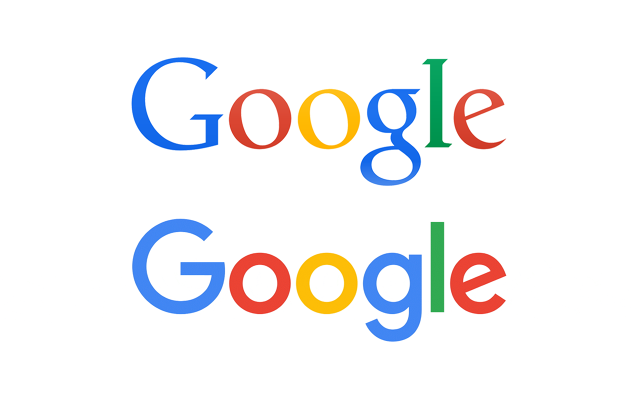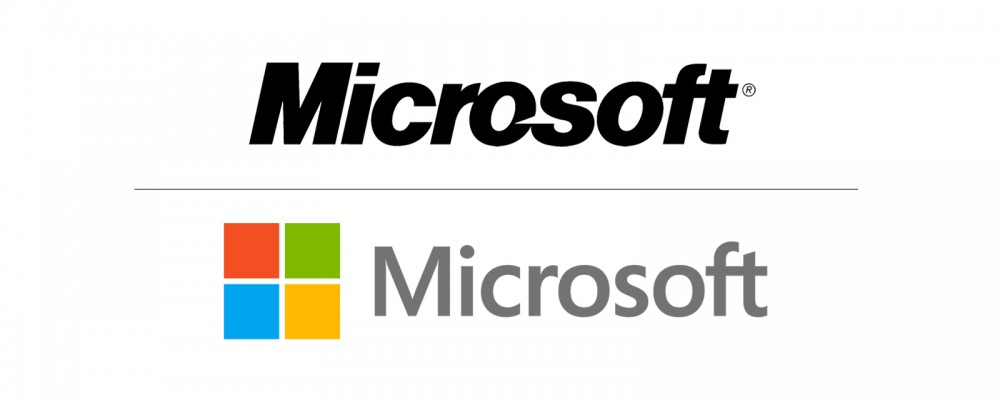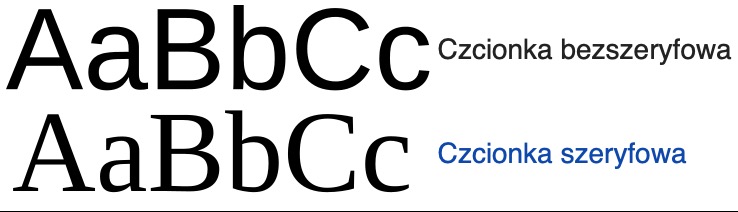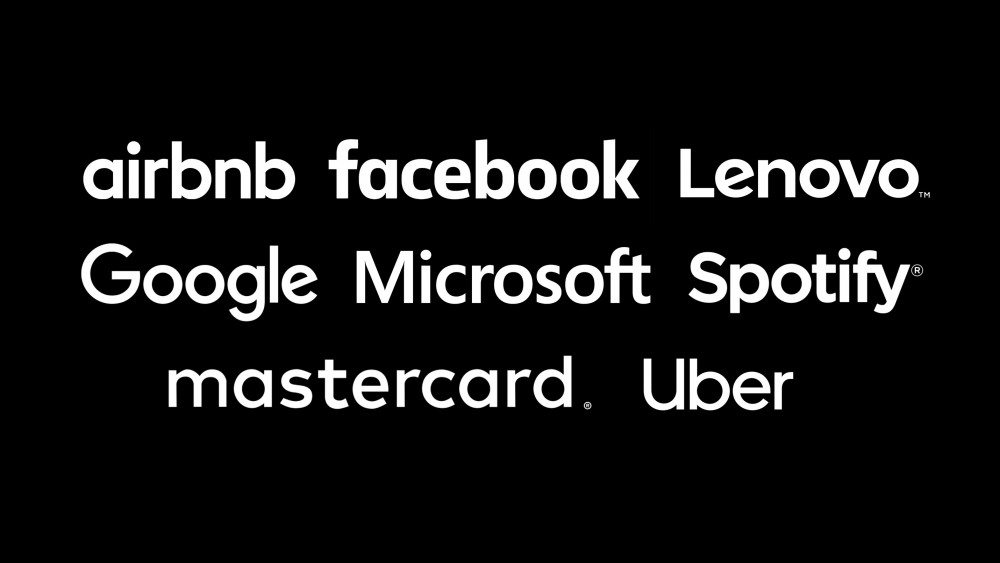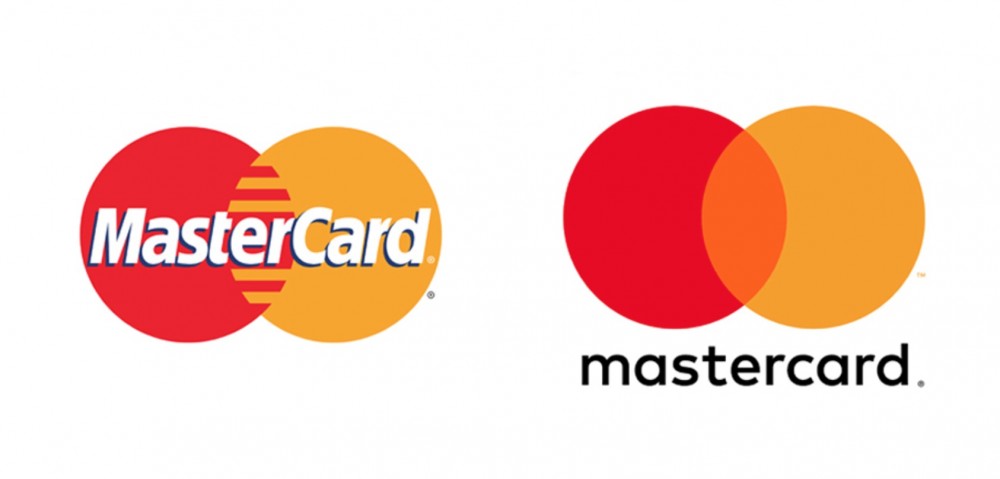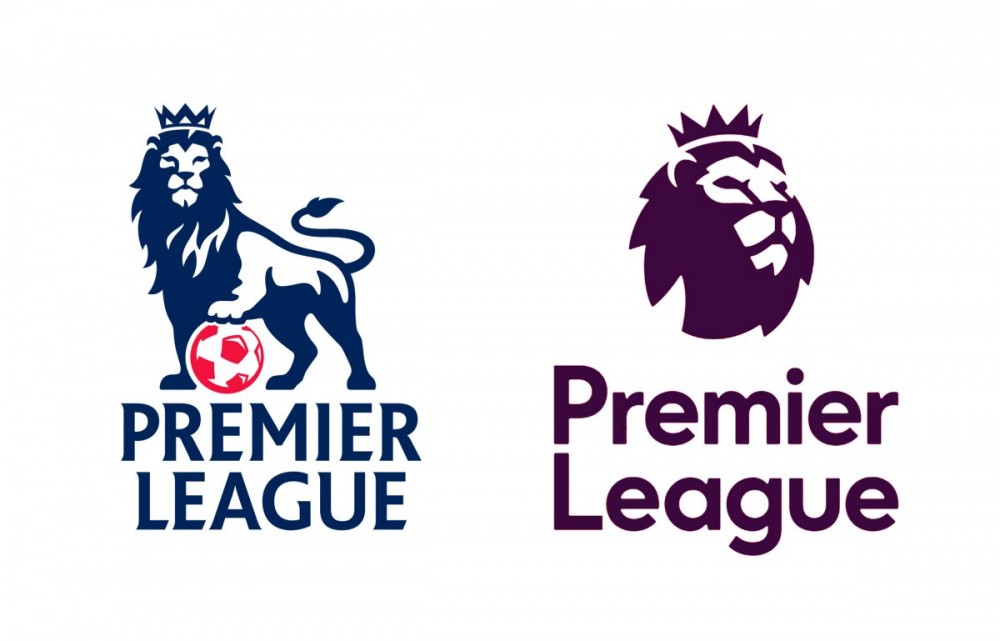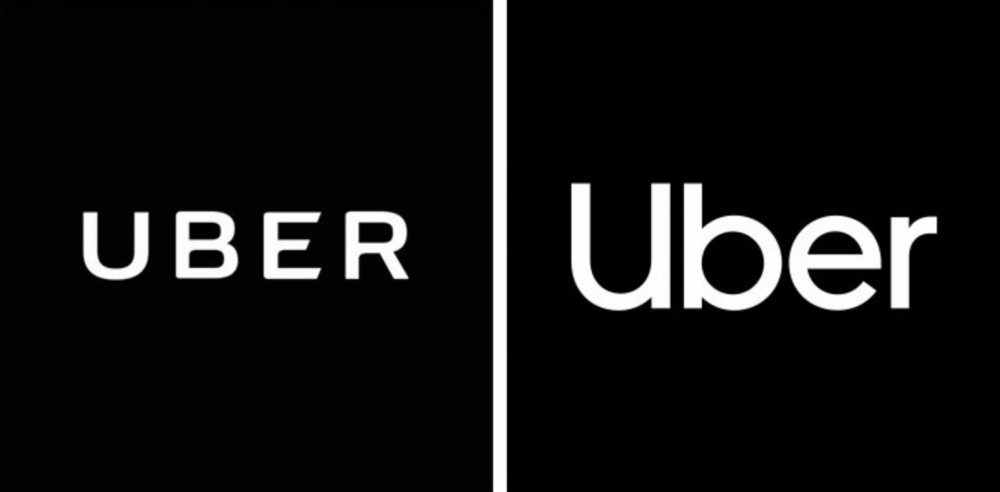
Dlaczego wszystkie nowe logotypy wyglądają tak samo?
Czy zastanawialiście się, dlaczego tak wiele firm decyduje się na uproszczenie swojego logo? Nie ma kwartału, by nie słyszeć o  rebrandingu dużej firmy. Nowe logotypy dążą do jednej wspólnej stylistyki, ale właściwie, dlaczego tak się dzieje?
Dlaczego wszystkie nowe logotypy wyglądają tak samo?
Niedawno napisał do nas czytelnik, będący project managerem w agencji reklamowej Upside. Agencja od 2010 r. posługuje się logo stworzonym przez dyrektora kreatywnego agencji.
Pojawił się jednak problem. Jak pisze project manager, hollywoodzka produkcja „The Upside” promuje się bardzo podobnym logo do agencji. W mailu pada stwierdzenie o „dokładnie takim samym znaku”, choć widać między nimi różnice. Film „The Upside” trafi na ekrany kin w 2019 r. i będzie amerykańską wariacją na temat francuskiego hitu „Nietykalni” z 2011 r.
Logo agencji wygląda następująco.
A tak prezentuje się wygląd materiałów promujących film.
Podobieństwo jest znaczące, ale czy można mówić o plagiacie?
Sądowe dochodzenie swoich praw może być w tym przypadku bardzo trudne. Oba logotypy są podobne, ale podobieństwo wynika z bardzo zbliżonego, niemal identycznego kroju pisma.
Sprawa jest o tyle ciekawa, że oba podmioty zastosowały najmodniejszą w ostatnich latach stylistykę, która jest chętnie wykorzystywana przez wiele firm, w tym przez największych gigantów świata IT. Do tego mamy identyczną nazwę, ale jest to najpewniej dziełem przypadku.
Ochrona logo firmy wynika wprost z prawa autorskiego i jest przyznawana na mocy ustawy, bez konieczności rejestracji znaku. Można też dodatkowo zarejestrować logo w urzędzie patentowym jako znak towarowy, ale nawet to nie chroni firmy w pełni, ponieważ ochrona tyczy wykorzystania logo w podobnych towarach lub usługach. Jeśli dwie agencje reklamowe miałyby bardzo podobne logo, można byłoby skutecznie dochodzić swoich praw. Co innego, gdy mówimy o agencji i filmie.
Logotypy dzisiejszych firm trudno od siebie odróżnić.
Tylko spójrzcie na zestawienie, które przygotowałem.
Takich przykładów jest znacznie więcej. Mamy różne grubości fontów, ale logotypy pozbawione sygnetu są do siebie niebywale podobne. Nie ma w tym żadnego przypadku. Coraz więcej firm przechodzi rebranding, który zbliża logotypy do jednej, wspólnej stylistyki. Spójrzcie tylko na kilka przykładów z ostatnich lat.
Dlaczego logotypy są do siebie tak podobne?
W pierwszej chwili można pomyśleć, że nadmierne upraszczanie bierze się z chęci oszczędności, bo przecież ile może kosztować zaprojektowanie zwykłego napisu zrobionego fontem Arial, lub podobnym bezszeryfowym krojem? To błędna logika, bo koszty rebrandingu w dużych firmach IT są przepotężne, nawet jeśli zmiany są niewielkie.
Różnica między fontem bezszeryfowym i szeryfowym; źródło: Wikipedia.
Skąd w takim razie podobieństwo logotypów? W dużej mierze wynika to z popularyzacji smartfonów. Dawniej logotypy były pokazywane na wydrukach, na banerach, czy w siedzibach firm. Później trafiły do internetu, ale były oglądane na dość sporych ekranach komputerów. Wszystko zmieniło się w erze mobilnej. Nagle logotypy muszą wyglądać świetnie na bardzo małych powierzchniach. Fragment górnej belki strony internetowej może mieć na smartfonie mniej niż centymetr, a logo na tym obszarze musi być czytelne i rozpoznawalne.
Co więcej, logo musi być wyraźne na przeróżnych konfiguracjach przekątnej ekranu i rozdzielczości. Musi wyglądać świetnie zarówno na nowoczesnym smartfonie z ekranem o kosmicznym zagęszczeniu pikseli, jak i na starszym urządzeniu, gdzie piksele są widoczne gołym okiem.
Jest to główny powód przechodzenia na bezszeryfowe fonty o podobnej stylistyce. Taki krój po prostu sprawdza się w dzisiejszym świecie, bo pasuje zarówno do druku, jak i do wyświetlania w różnych rozdzielczościach. Przykład rebrandingu Facebooka pokazuje, jak bardzo istotna jest ta kwestia. Tylko spójrzcie, jak nieznacznie zmienił się logotyp serwisu, a mimo to Facebook wdrożył zmianę.
Nowy kształt litery „a” został wprowadzony właśnie w celu zwiększenia czytelności na małych ekranach.
Firmy przestaje wyróżniać logotyp. Coraz większa waga przypada na rozpoznawalny sygnet.
Na logo składa się logotyp (zapis nazwy) oraz sygnet, czyli znak graficzny. Ten drugi w erze mobilnej staje się coraz ważniejszym elementem identyfikacji firmy, zwłaszcza w obszarze IT. Tylko spójrzcie na ekrany swoich smartfonów. Rozpoznajemy aplikacje tylko po sygnecie. Przeważnie dobrze wiemy, o jaką aplikację chodzi, bez konieczności czytania podpisu pod nią. Rzut oka wystarczy, by rozpoznać Gmaila, Spotify, czy Facebooka.
Wielcy świata IT mogą sobie pozwolić na modne ujednolicenie kroju logotypu, bo nie zaszkodzi to rozpoznawalności marki. Jeśli na ten sam krok decydują się mniejsze podmioty, to biorą na siebie większe ryzyko i nie powinny mieć pretensjo o to, że ich stylistyka jest zbyt podobna do logotypu innego podmiotu. Tym bardziej, jeśli firma nie ma wypracowanego mocnego sygnetu.